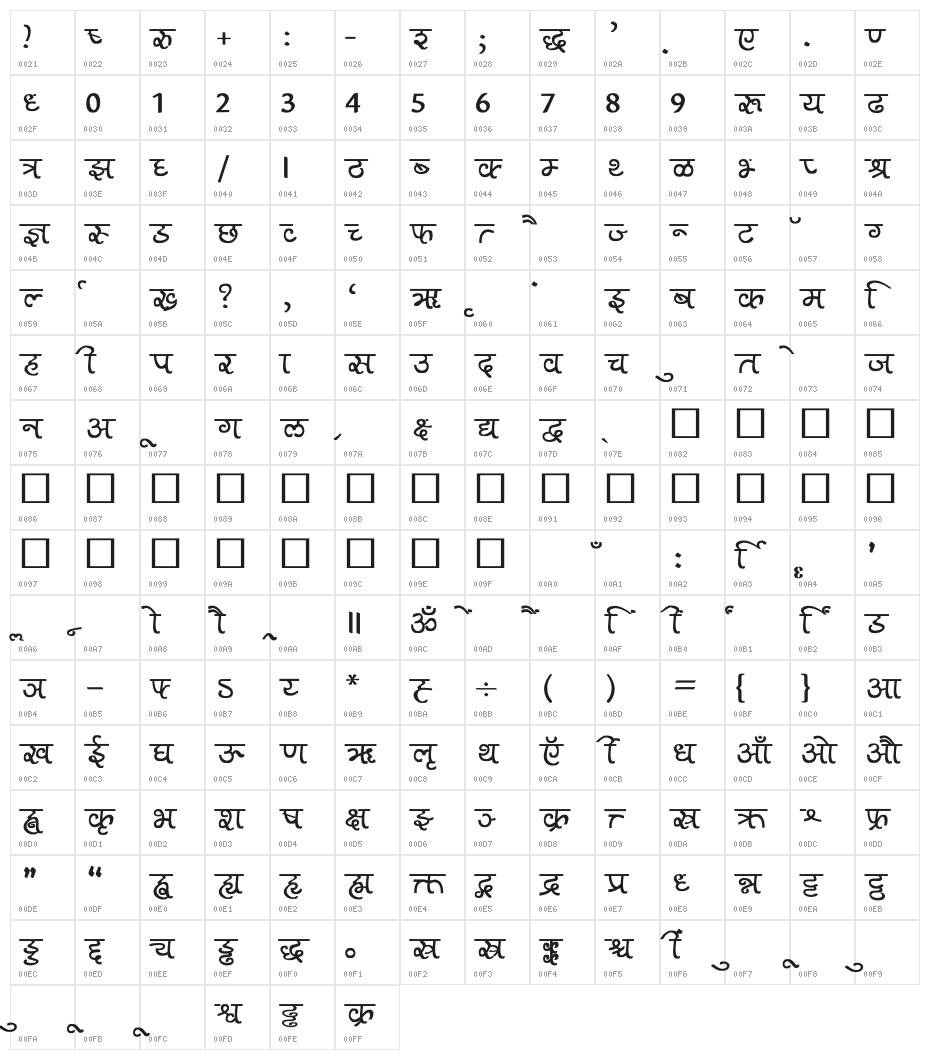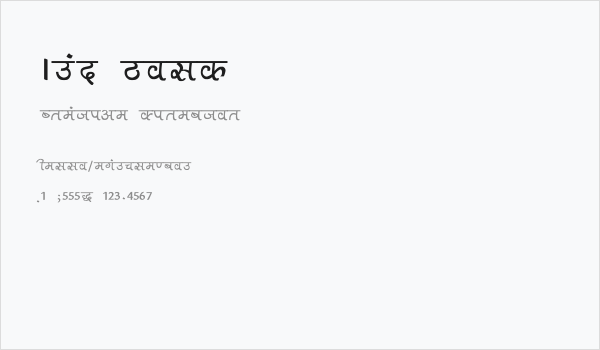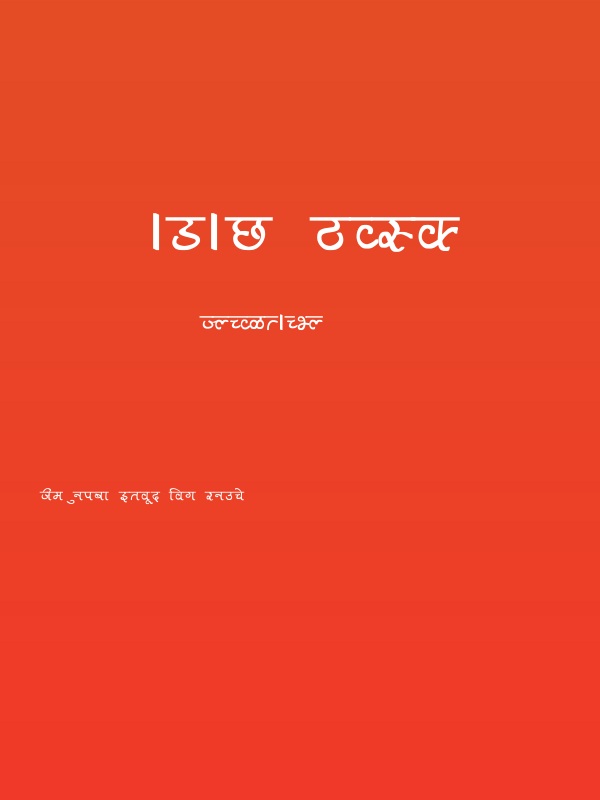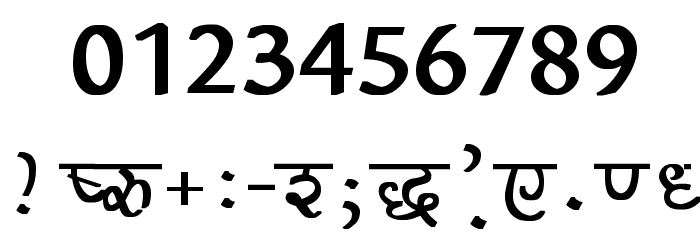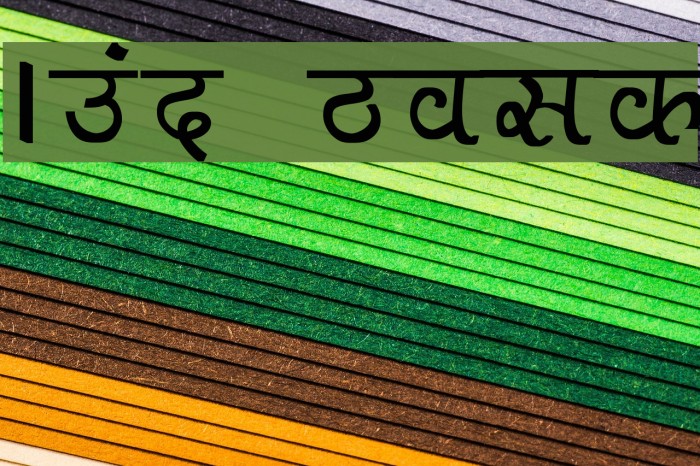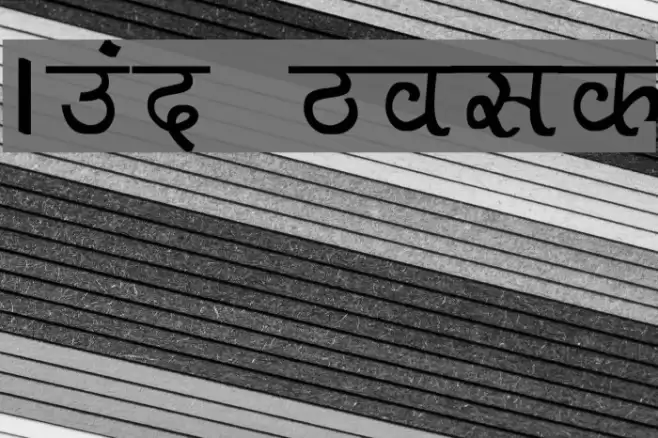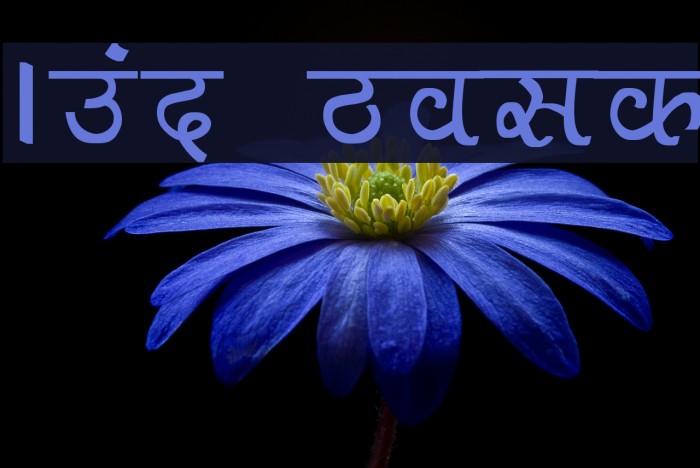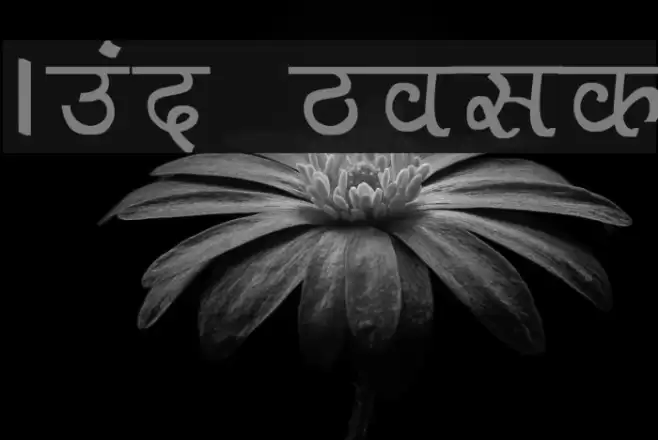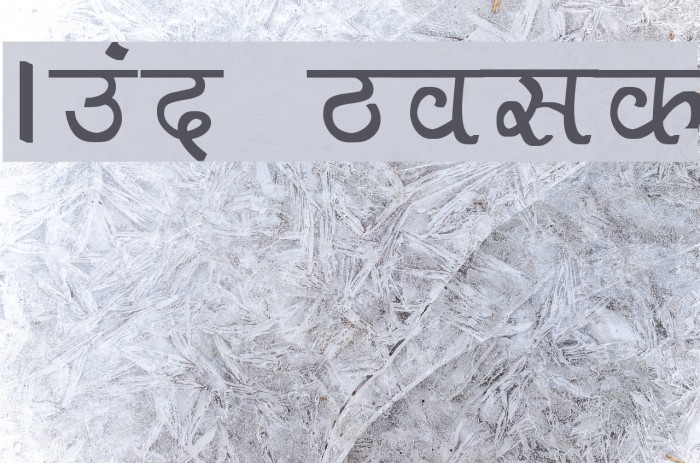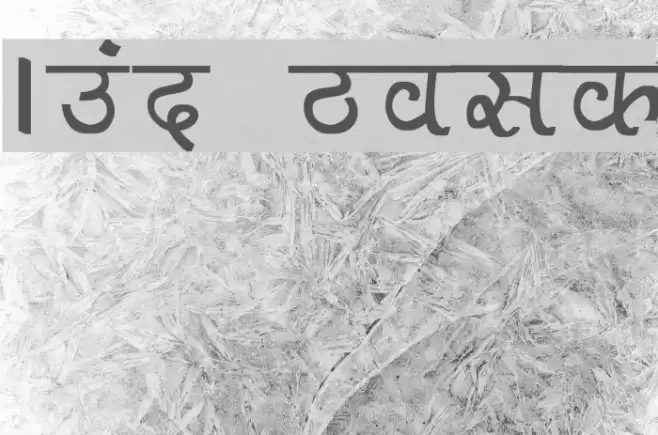
Aman Bold Font
| Общий стиль | Traditional |
| Область применения | Headlines, Signage, Cultural publications |
| Рекомендуемые проекты | Ideal for cultural publications, educational materials, signage, and any project requiring a traditional script style. |
| Автор | Fonts by TypeSETit |